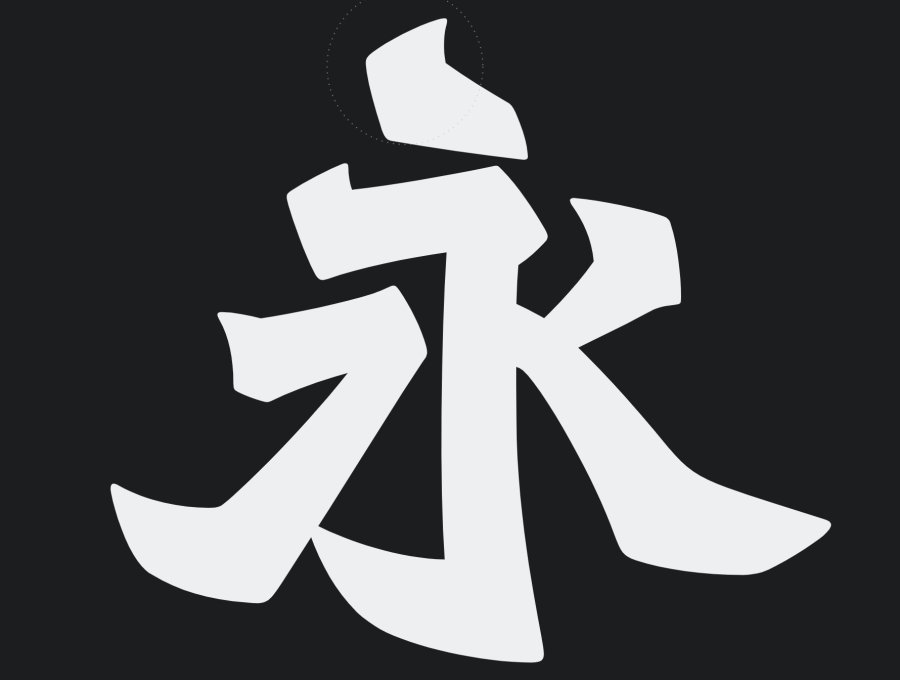
关于香港北魏真书:
二〇一二年由字体设计师、叁语设计合伙人/设计总监陈浚人发起,以设计思维分析北魏书法的历史文化和创作精神、北魏体在香港民间的应用研究,还有多年来利用当代字体设计演绎香港北魏的创作历程。二〇一八年夏联同设计编辑徐巧诗出版《香港北魏真书》,书中收录了南北朝魏碑、清代书法家赵之谦到四十至七十年代盛行香港的北魏招牌书法源流和艺术价値,访寻香港北魏书法家区建公、苏世杰的墨宝,于不同年代遍布香港城市街道和日常生活的北魏体应用实例,并首次专访独步香江的货车北魏体设计者杨佳;字体设计师陈浚人,利用电子向量曲线和字体设计原理演绎的当代「香港北魏真书」,亲自细说二十多项设计案例的创作历程。作者们还与多位本地设计创作人包括麦震东、谭智恒、柯炽坚和许瀚文等对谈系列,探究字体在城市和设计文化中的重要角色。
著书出版是研究计划的其中一环,香港北魏真书计划希望在未来与不同界别的创作人、书法家、历史文化专业、设计师、学生和大众交流分享,集思广益,并积极筹划网上众筹计划,目标是集资自组专业的设计团队,专注研究、设计和造字,让香港北魏真书发展成为一套完整的中文字库。